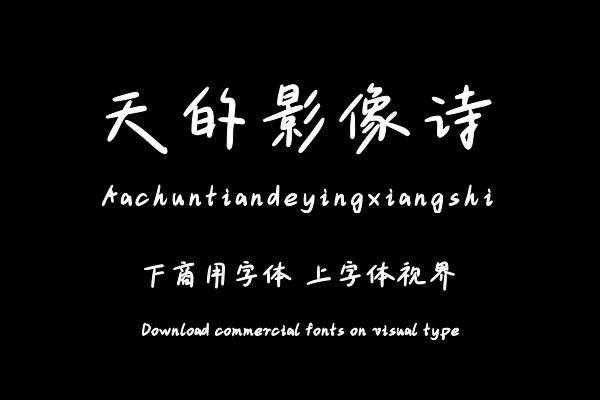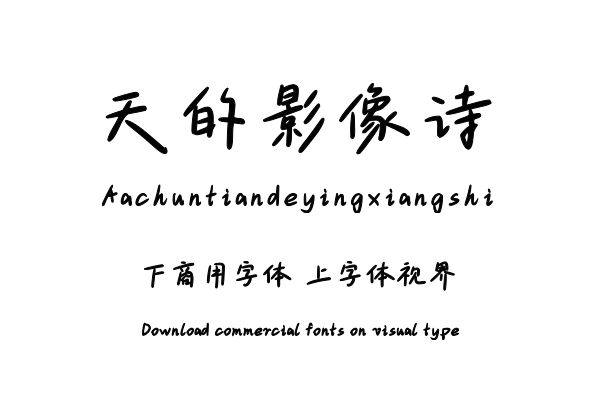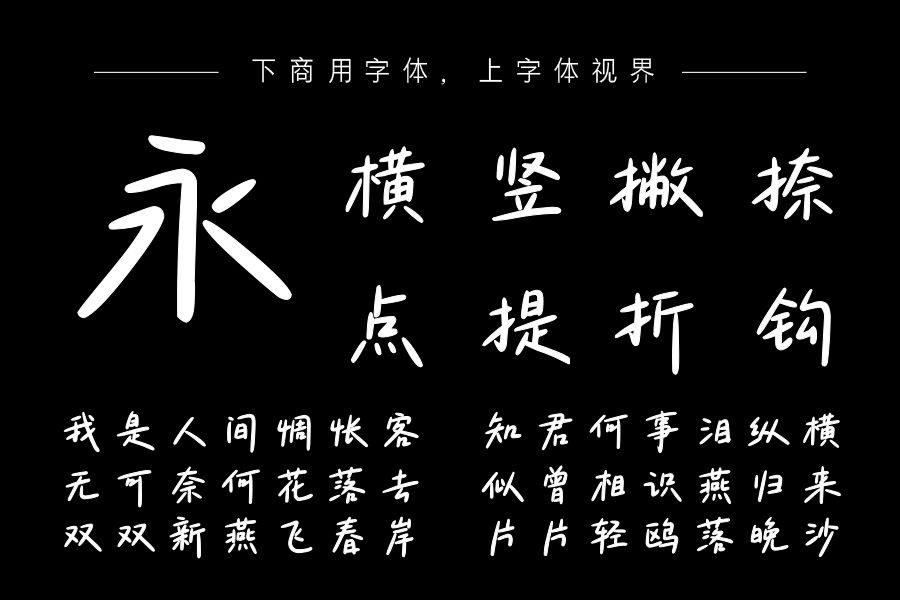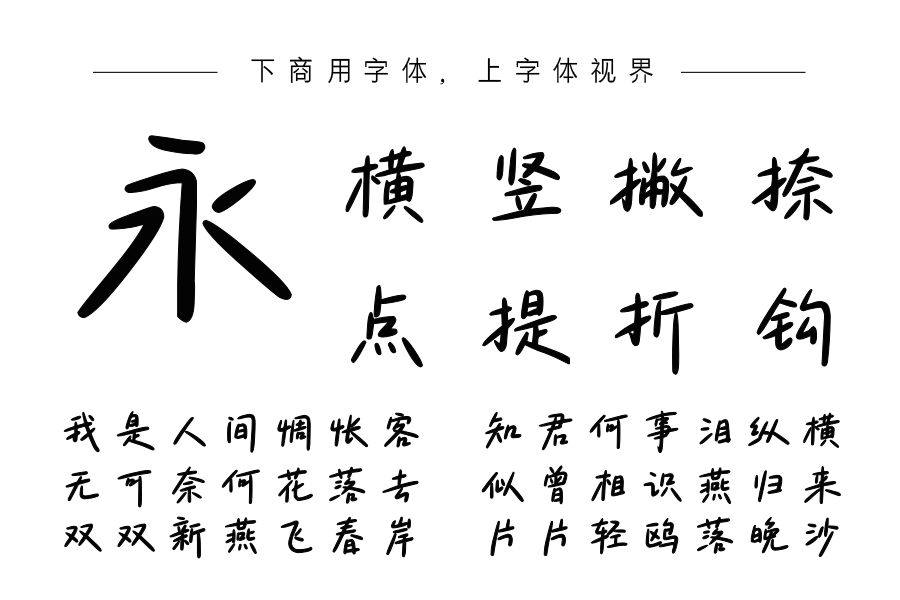
Aa春天的影像诗是一款文艺清新的手写字体,笔画舒展纤长,轻盈灵动,充满春日愉悦又慵懒的气质。适用于手写信、专辑标题、照片装饰、视频字幕等,用于传递温度感与自由轻......购买须知:“下载服务费”与“字体VIP”所获得字体 仅用于个人非商用, 商用请联系付费授权。本字体为电脑用字,手机没有root权限不支持直接手机换字(手机如何root,请自行百度搜索教程)。购买前请先 了解清楚后再付款 ,字体为虚拟产品无法回收 一旦购买不支持退款。